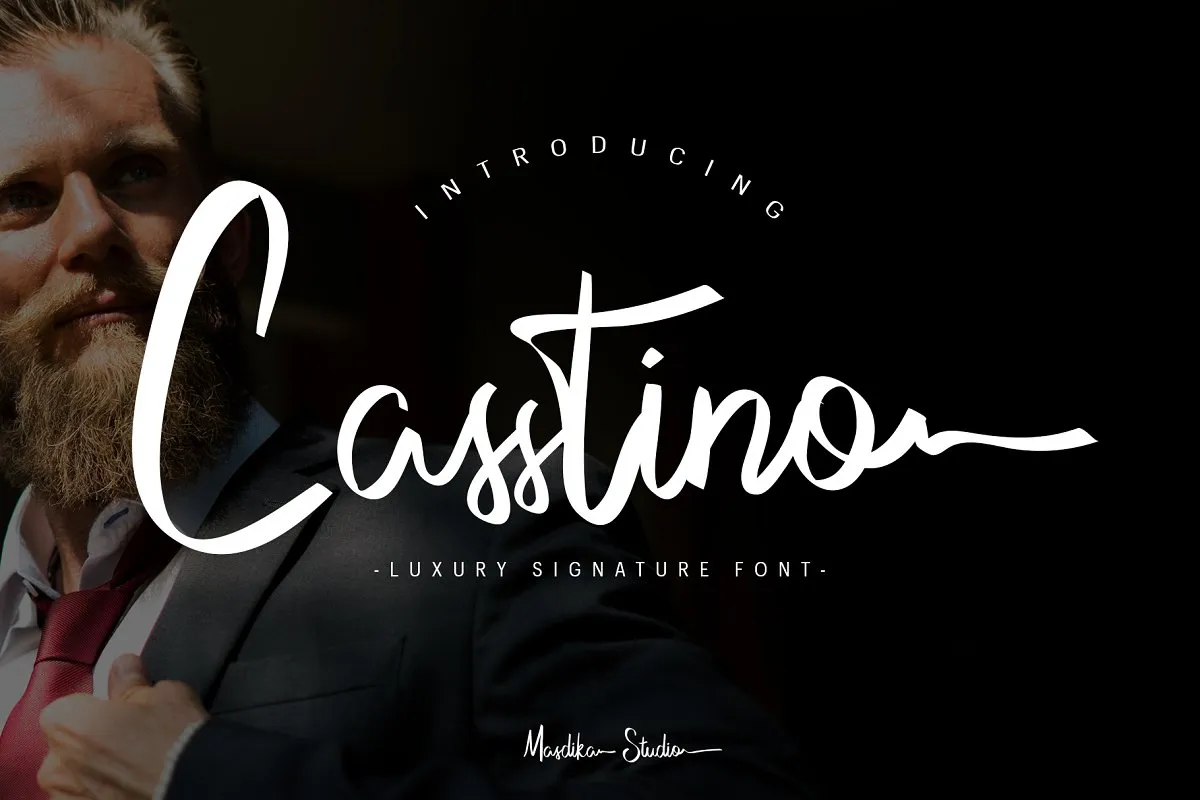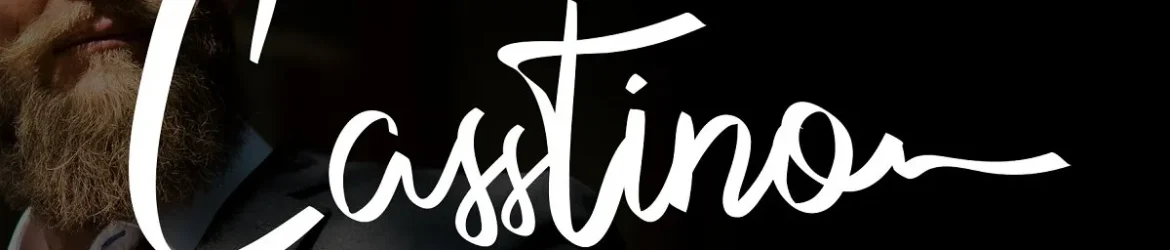
A Casstino Handwritten Font é uma nova escolha para projetos que exigem sofisticação com um toque autêntico. Introduzida pela designer 0001themes, essa font script apresenta um estilo elegante e cuidadosamente elaborado. O design leva em consideração os detalhes finos dos traços e o realismo de suas transições de linha, dando ao seu projeto uma personalidade única. Com a Casstino Font, você pode adicionar um toque luxuoso e pessoal a qualquer texto ou logomarca que estiver criando, seja para cartões de convite, editoriais de moda ou até mesmo para o design do site da sua empresa. Estando disponível como uma fonte script, ela se destaca por seu acabamento cuidadosamente elaborado, oferecendo um visual único e profissional a seus projetos visuais.